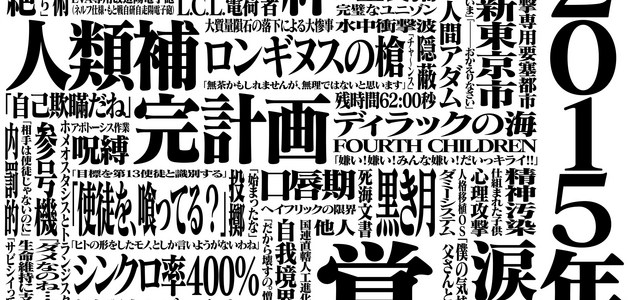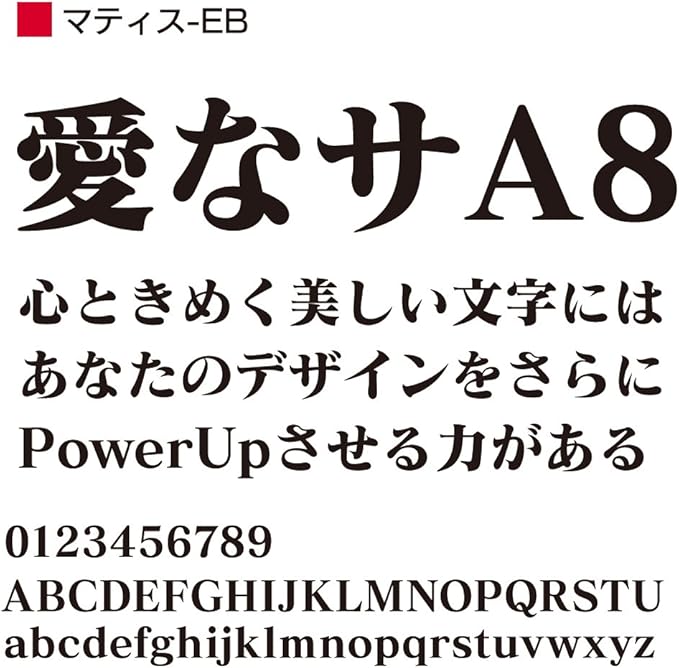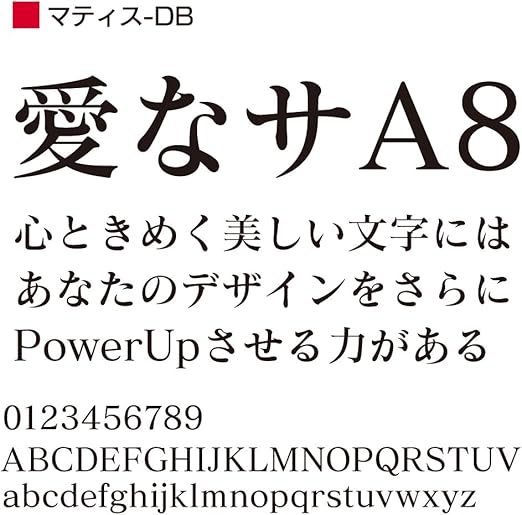
マティス フォント
フォントを見る マティス EB ベーシックな部分を大切にしたデザインの中にも、古さを感じさせないシャープさと柔らかで優しい曲線の表情を合わせ持った明朝体です。. エヴァンゲリオン公式フォント マティスEB TrueType版 数量限定!在庫限り!お早めにお買い求めください! 「新世紀エヴァンゲリオン」において「時に、西暦15年」「使徒、襲来」など、黒字に白抜きの文字表現で大反響を呼び、ファンの間では“エヴァ明朝”とも呼ばれる「マティスEB」が. エヴァンゲリオン公式フォント マティスEB TrueType版 数量限定!在庫限り!お早めにお買い求めください! 「新世紀エヴァンゲリオン」において「時に、西暦15年」「使徒、襲来」など、黒字に白抜きの文字表現で大反響を呼び、ファンの間では“エヴァ明朝”とも呼ばれる「マティスEB」が.
どうも。エヴァが放送されたときリアルで14歳でA10神経全開だった、するぷ( @isloop )です。 先日、ついにエヴァに使われているフォント「マティス Pro EB」(通称俺明朝)を購入しました。 しかし、このフォントをそのまま使うとどうもエヴァっぽくないのです。. 通常フォントというものは非常に高価な製品。 しかし、「マティスeb」を個人利用に限り4,600円(税別)という安価で提供する特別パッケージが、「エヴァンゲリオン公式フォント マティスeb版」です。 フォントワークス社のサイトから購入すれば、決済後にダウンロードでき、後日cdromと. (2/7追記) こんにちはゆむらです。 タイトル通りです。暇だったので調べてみました。 くろかね eb パズドラといえばこのフォント。 太めのエレメントの端をスパッと落とし、鉄のように黒く力強い雰囲気の中に、どこか優しさをもっている書体。.
マティス (Matisse)は、 フォントワークス が発売した 明朝体 およびその フォント 製品。 デザイン は ロダン を手がけた 佐藤俊泰 による。 1991年 に Macintosh DTP 用 PostScript フォントとしてリリースされた。. マティスeb あの某有名アニメで使われたフォント。 「マティス」を選んで太字にチェックを入れると使うことができます。 黒背景に白字・赤字で雰囲気はバッチリ。 文字の大きさを変えたり、縦書き・横書きを組み合わせてみるとなおグッド!. マティスeb あの某有名アニメで使われたフォント。 「マティス」を選んで太字にチェックを入れると使うことができます。 黒背景に白字・赤字で雰囲気はバッチリ。 文字の大きさを変えたり、縦書き・横書きを組み合わせてみるとなおグッド!.
マティスeb あの某有名アニメで使われたフォント。 「マティス」を選んで太字にチェックを入れると使うことができます。 黒背景に白字・赤字で雰囲気はバッチリ。 文字の大きさを変えたり、縦書き・横書きを組み合わせてみるとなおグッド!. エヴァンゲリオン公式フォント マティスEB TrueType版 製品・サービス TVシリーズで使⽤された「EVAマティスクラシック」と、新劇場版で使⽤された「EVAマティススタンダード」の2種類のフォントデータを収録。. フォントワークスは、 文字の力を 最大化していく 日々書き換えられ続けるコミュニケーションを予見し、時代にも環境にも合った「文字」を提供することで、あらゆる人の日常に新しい価値を生み出そうとしています。.
フォントを見る マティス M ベーシックな部分を大切にしたデザインの中にも、古さを感じさせないシャープさと柔らかで優しい曲線の表情を合わせ持った明朝体です。.